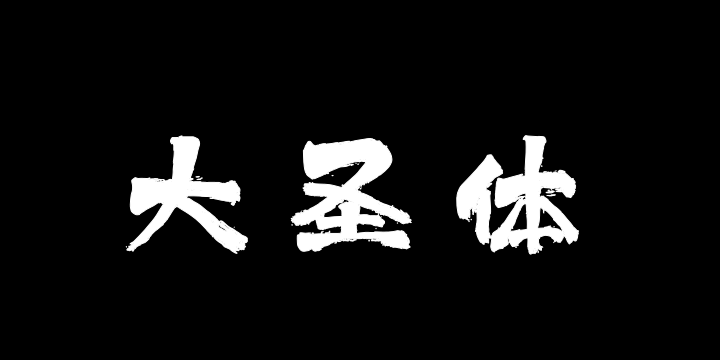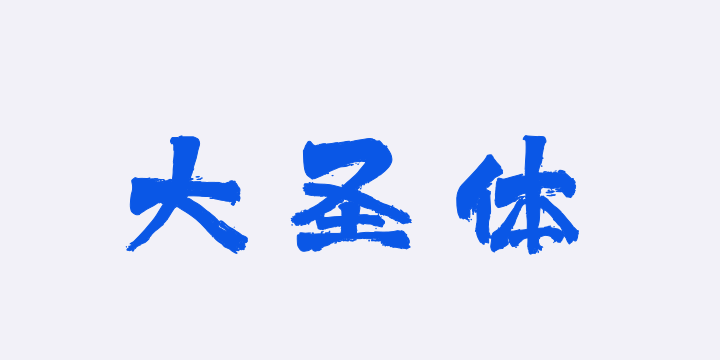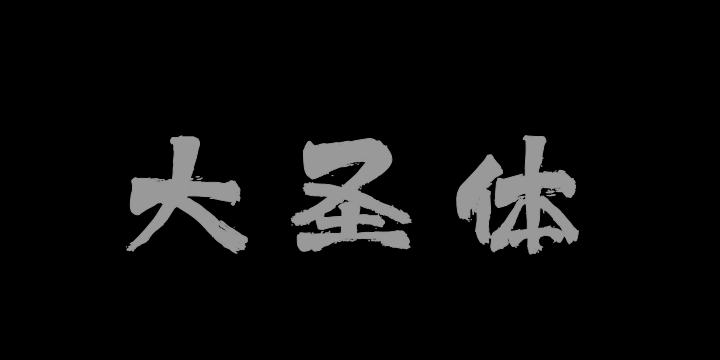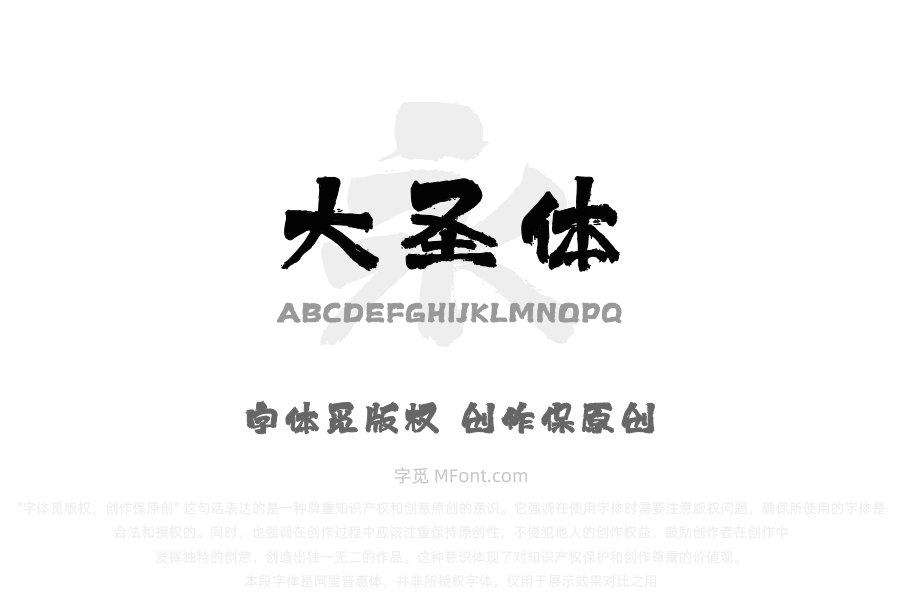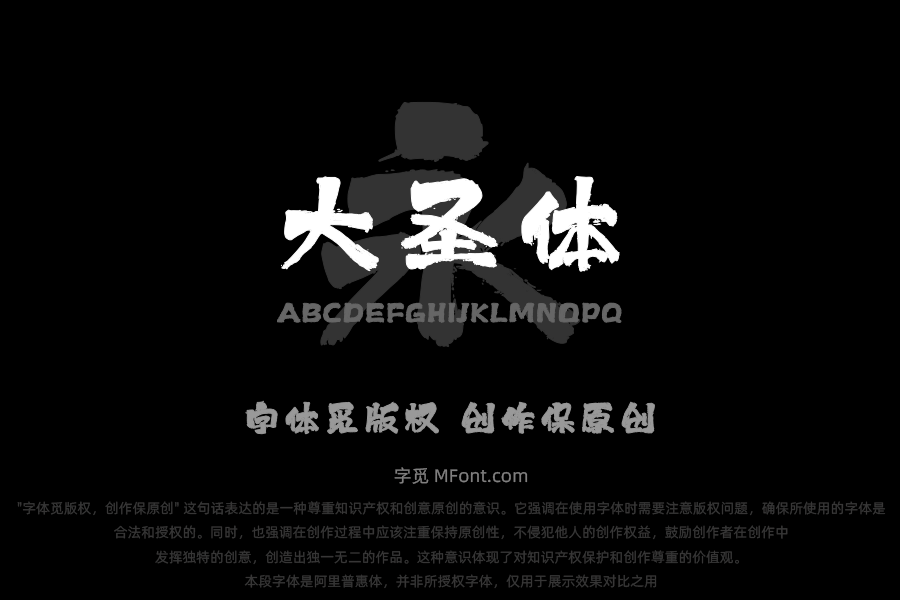
字体全名: 上首大圣体
字体简介: 上首大圣体,立足对中国传统书法艺术的敬畏与创新探索,融合现代字体设计的规范性与实用性,打造出兼具艺术感染力与视觉识别性的独特字体。笔画粗细变化自然灵动,起笔、收笔处保留书法 “提按顿挫” 的韵律感 —— 枯笔的涩意、顿笔的厚重等细节被巧妙还原,传递出书法艺术特有的生动质感。在遵循汉字传统间架结构的前提下,通过笔势的张扬与凝练,营造出大气磅礴、庄严肃穆的视觉张力。融入 “大圣” 所象征的豪迈刚健、充满力量感的精神内核,笔画间透着果敢与劲挺。适用于搭配标志、广告标语、商业广告等高端属性。